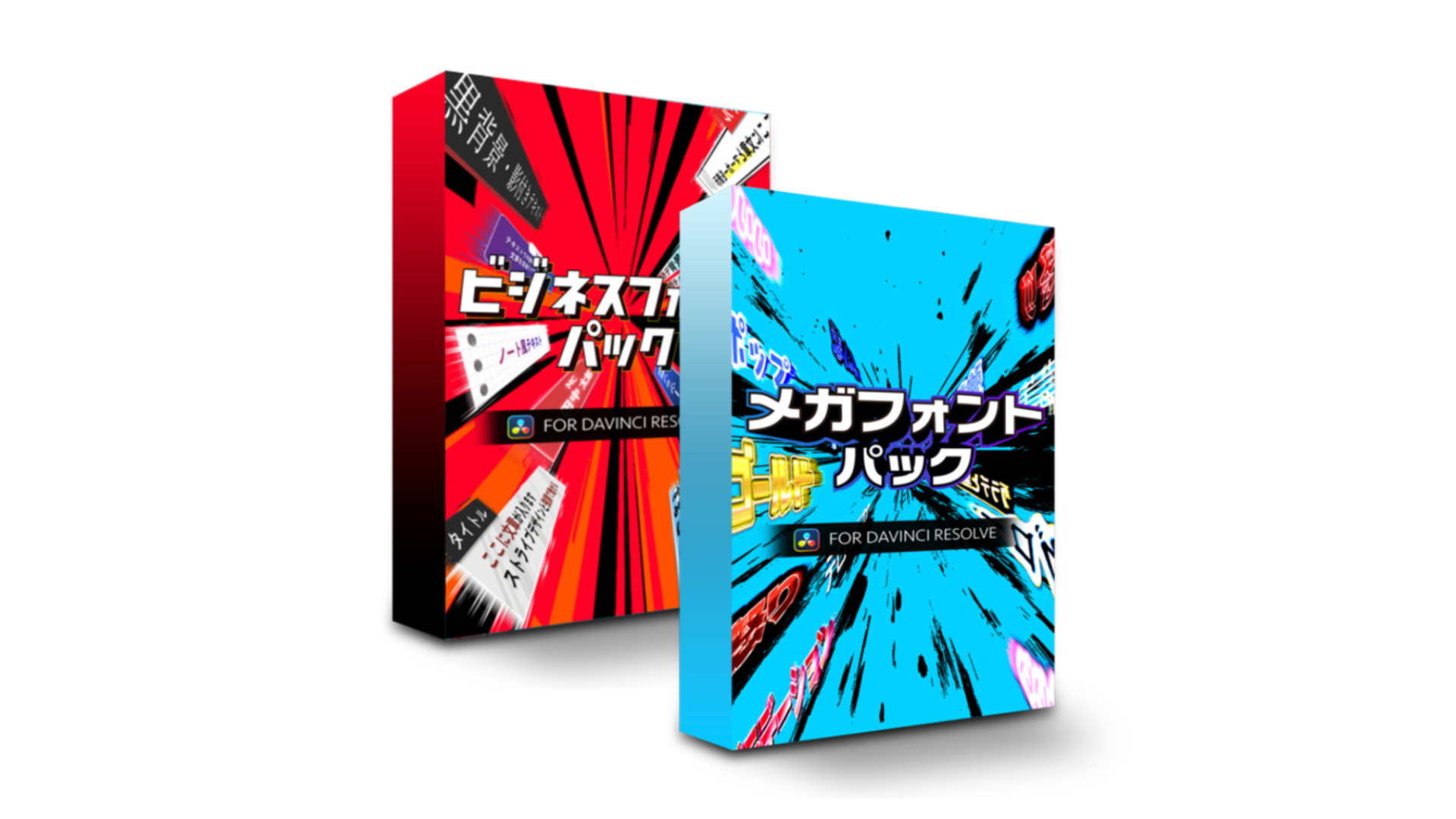
人気のフォントパックをセットにした「Master Font Bundle」を発売開始
Visual Parkは、人気製品である「Business Font Pack」と「Mega Font Pack」をセットにした新製品「Master Font Bundle」の販売を開始いたします。
2つの人気フォントパックをひとつに
Master Font Bundleには、Visual Parkが提供する以下の2製品が含まれます。
Business Font Pack
ビジネス・教育・企業案件向けの映像制作に特化したフォントテンプレート集です。清潔感や信頼感を重視したタイトルデザインを多数収録し、YouTube動画から企業VP、セミナー映像まで幅広いジャンルに対応します。
Visual Parkオリジナルフォントを活用した高品質なテンプレートにより、編集者はデザイン制作にかかる時間を大幅に削減しながら、統一感のある映像表現を実現できます。
Mega Font Pack
YouTubeやSNS動画向けに開発された大型フォントパックです。
インパクトのあるサムネイル風デザインからバラエティテロップ、エンタメ系タイトルまで、多彩なスタイルを収録。視認性と演出効果を両立し、個人クリエイターから商業案件まで幅広く活用できます。
動画のジャンルやテイストに応じて使い分けることで、映像表現の幅を大きく広げることが可能です。
すべての動画編集者に向けたフォントライブラリ
Master Font Bundleは、企業案件向けの洗練されたデザインと、YouTube向けの高い演出力を兼ね備えたフォントコレクションです。
情報を正確に伝えるビジネス動画から、視聴者の目を引くエンタメ動画まで、あらゆる制作シーンに対応できる構成となっています。
これから動画編集を始める方はもちろん、日常的にクライアントワークを行う映像クリエイターにとっても、長期的に活用できる実践的なライブラリとしてご利用いただけます。